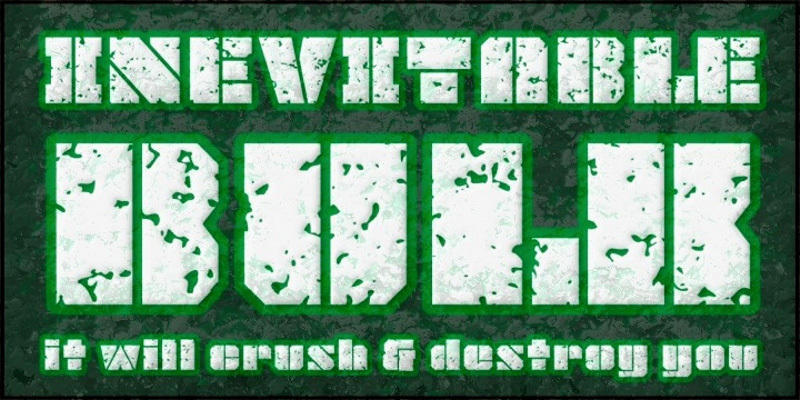
JLS OverKill Grunge, entworfen von Mike Adkins und James Stirling, ist eine kostenlose, verwitterte Militär-Display-Schrift. Ihre blockhaften Großbuchstaben zeichnen sich durch quadratische Formen und tief eingearbeitete Schablonenschnitte aus. Über die wuchtigen schwarzen Buchstaben verlaufen weiße Abplatzer, Kratzer und beschädigte Stellen.
Plakatdesigns stellen die überzeugendste Anwendung dar, insbesondere für Kampfspiele, Action-Events und harte Musikpromotionen. Die beschädigte Textur eignet sich zudem für taktische Merchandise-Artikel und robuste Produktverpackungen. Auf Magazincovern und in der Editorial-Grafik kann sie ein abgenutztes industrielles Thema etablieren, bevor der begleitende Text beginnt.